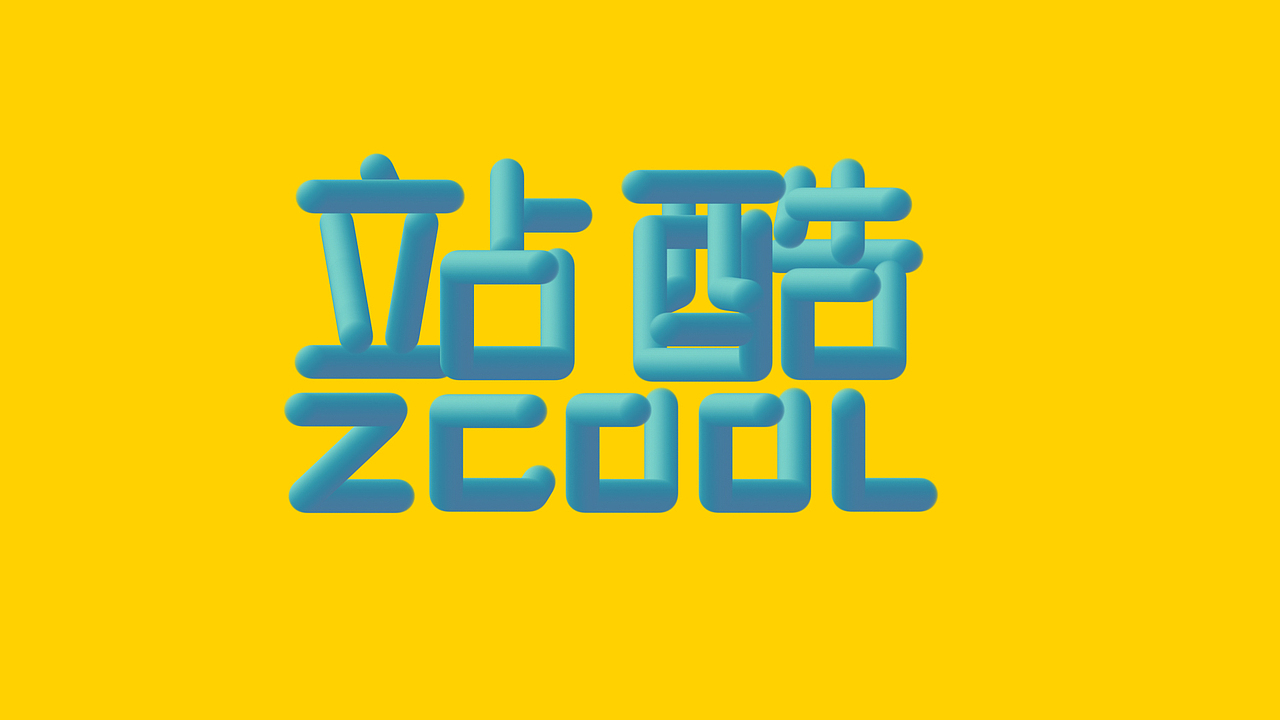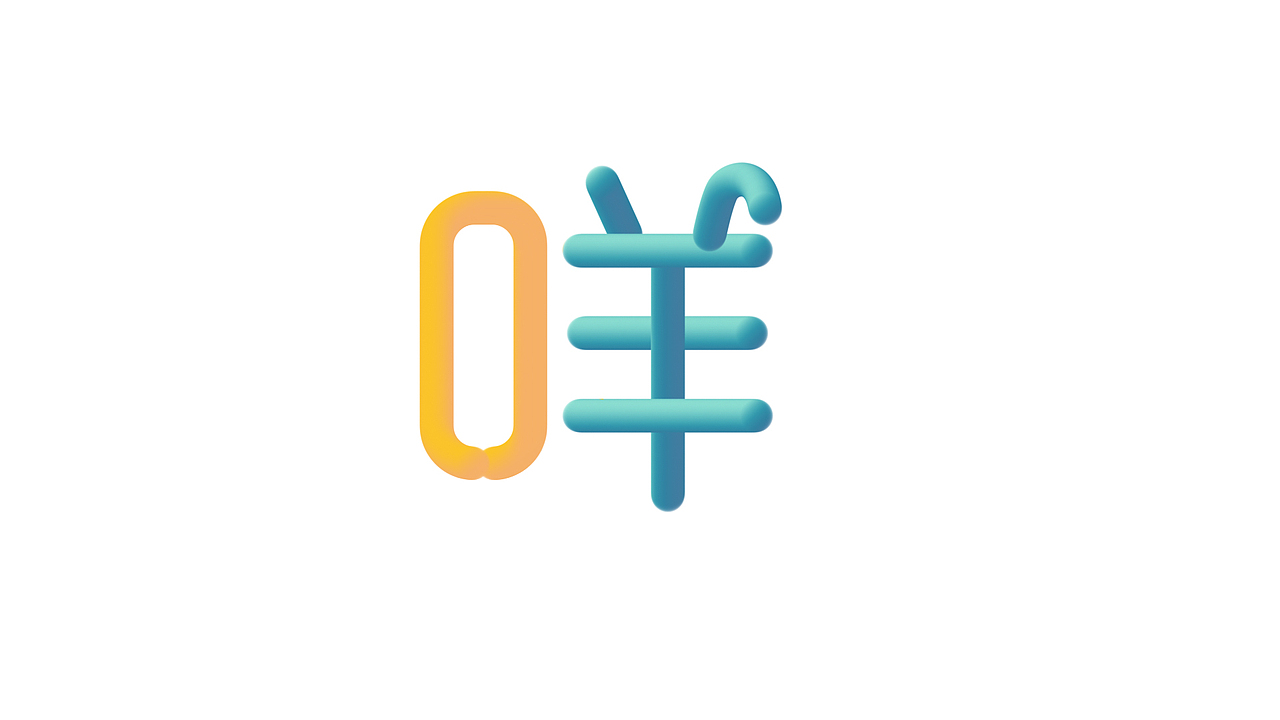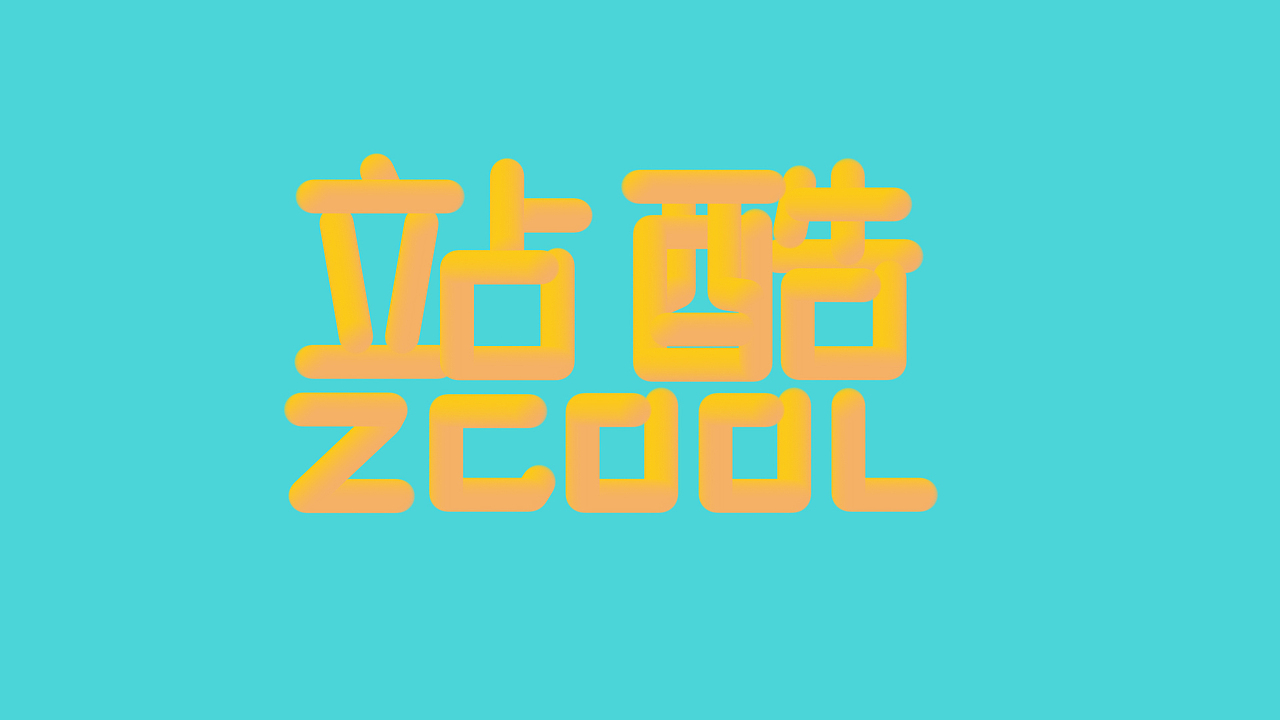
3D线条字体
3D线条字体(图ZODY2ODgyNjQ=) - 字体/字形 - 站酷设计师阿勇咩原创素材 - 站酷ZCOOL
3D线条字体(图ZODY2ODgyNzI=) - 字体/字形 - 站酷设计师阿勇咩原创素材 - 站酷ZCOOL
3D线条字体(图ZODY2ODgyODQ=) - 字体/字形 - 站酷设计师阿勇咩原创素材 - 站酷ZCOOL
3D线条字体(图ZODY2ODgzMTI=) - 字体/字形 - 站酷设计师阿勇咩原创素材 - 站酷ZCOOL